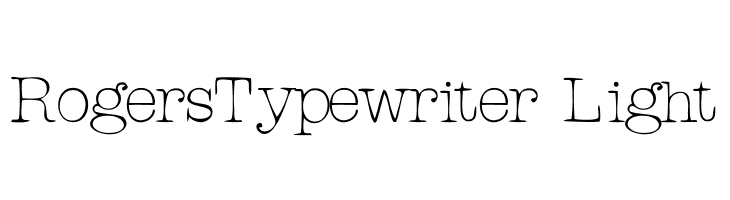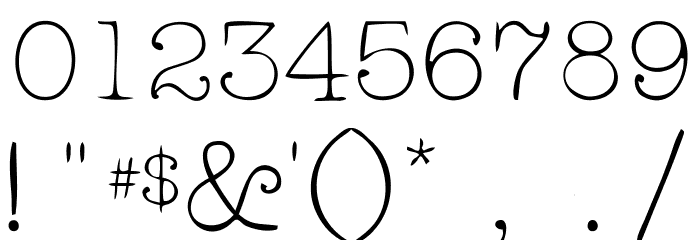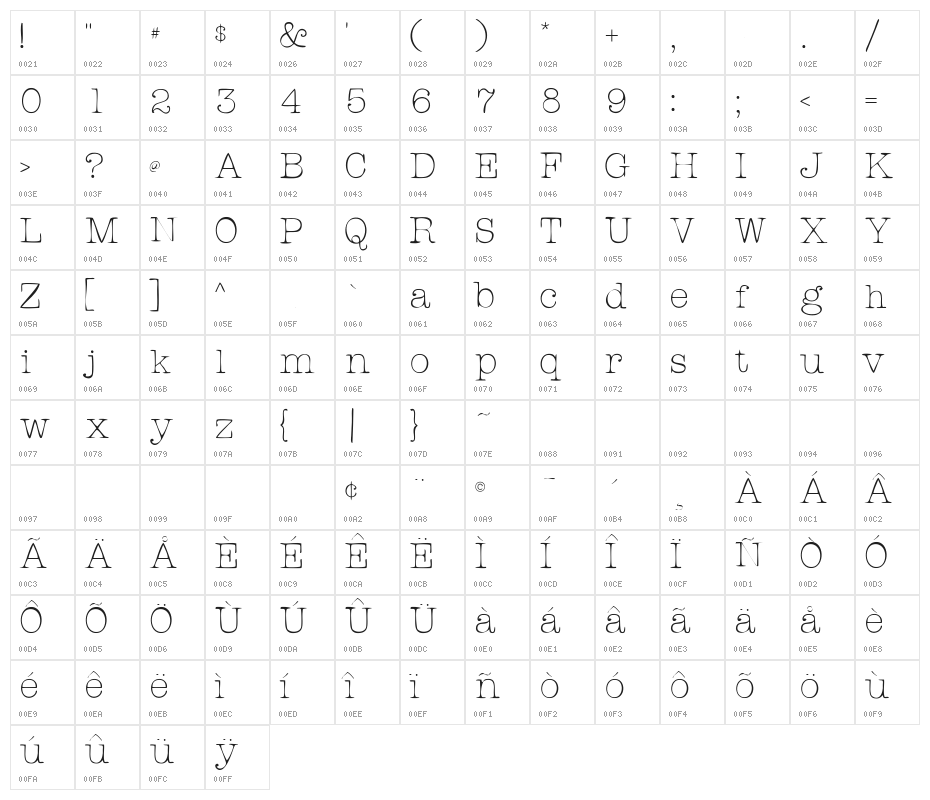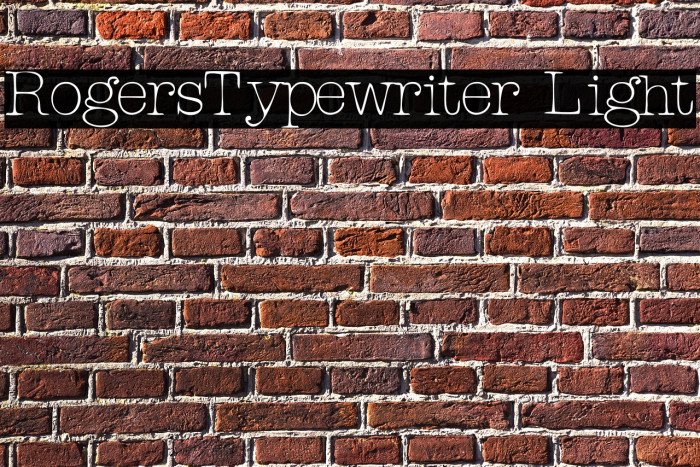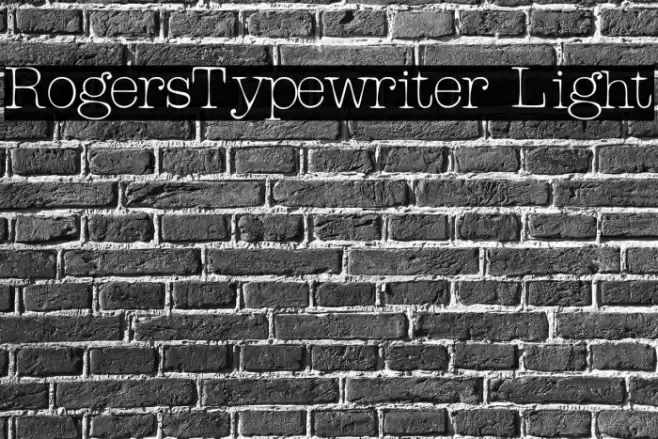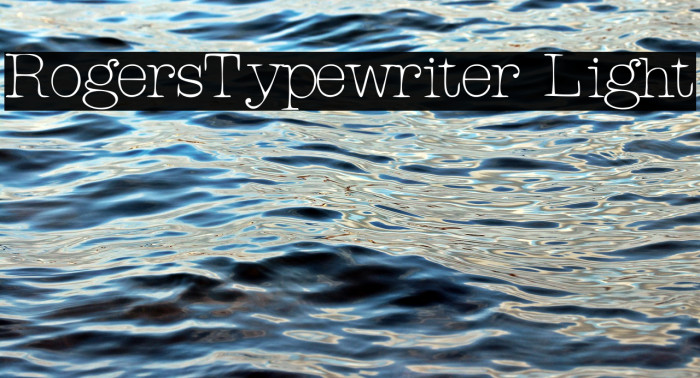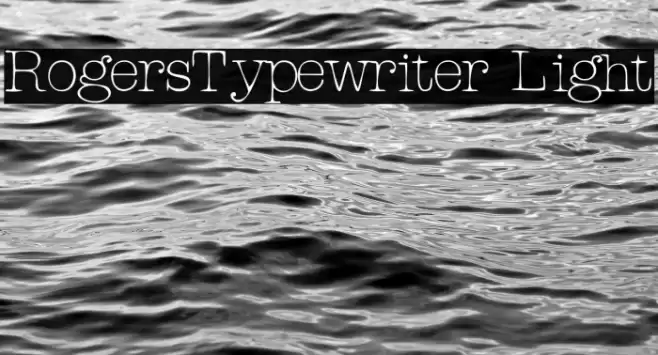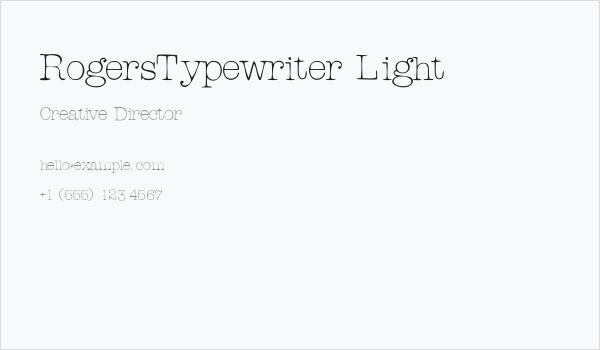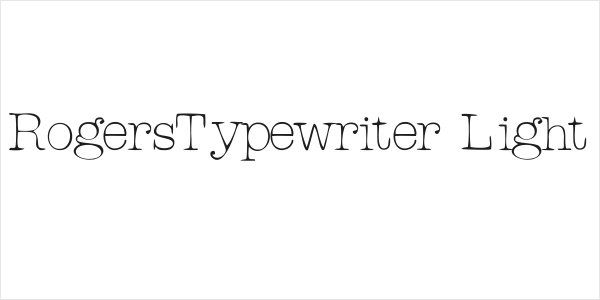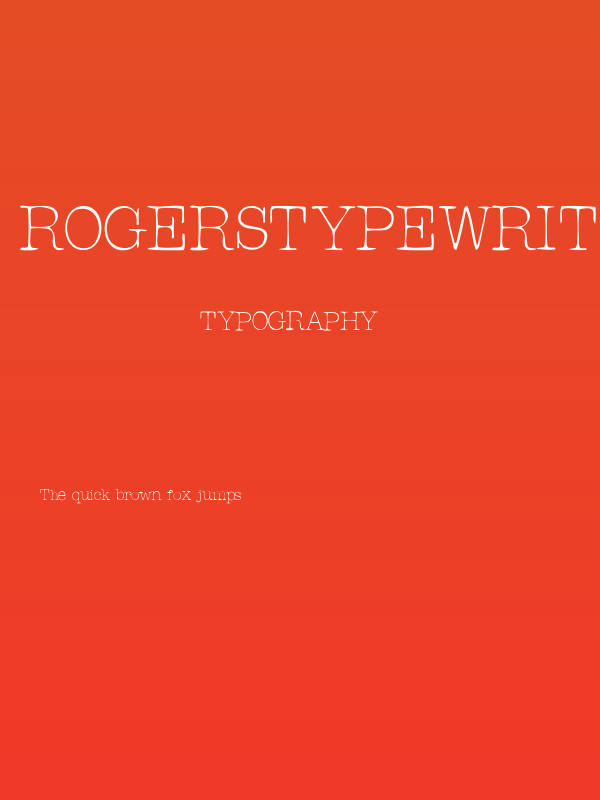
RogersTypewriter Light Font
| Projetos propostos | Ideal for vintage-themed designs, typewriter-style documents, retro posters, and creative writing projects. |